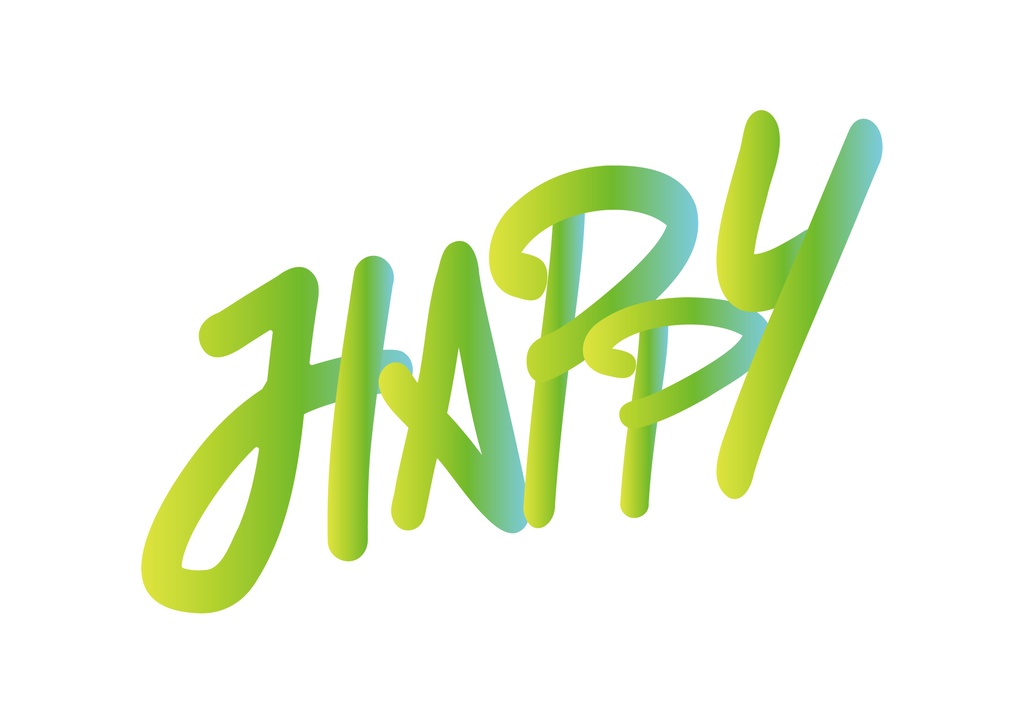
【商用可・無料配布】手書きの衝動をデザインに!「タギングフォント」
こんにちは! 私たちは、名古屋市星ケ丘にあるクリエイティブ特化のB型就労継続支援事業所「でじるみ名古屋星ケ丘」です。 この度、当事業所の利用者さんが心を込めて制作した、オリジナルの手書きフォント「タギングフォント」を無料配布させていただくことになりました! ◆ フォントの特徴 ストリートカルチャーから飛び出してきたような、ラフで力強い手書き感が魅力のフォントです。 一文字一文字にクリエイターの個性が光り、あなたのデザインにクールなアクセントとインパクトを与えます。 《こんなシーンにオススメ!》 動画のテロップやYouTubeのサムネイル 同人誌のタイトルや奥付 イベントのフライヤーやポスター オリジナルのTシャツやグッズ制作 SNS投稿の画像加工 など あなたのクリエイティブな活動の相棒として、ぜひご活用ください! ◆ でじるみ名古屋星ケ丘について 私たちは、デザイン、イラスト、動画編集など、一人ひとりの「好き」や「得意」を仕事につなげるサポートをしています。 このフォントは、利用者さんが日々スキルを磨き、情熱を注いで作り上げた努力の結晶です。 このフォントをダウンロードし、使っていただくことが、利用者さんたちの自信と、さらなる創作活動への大きな励みになります。 もしよろしければ、商品ページの「スキ!」やSNSでのシェアで応援していただけると、スタッフ・利用者一同、大変嬉しく思います。 ◆ 利用規約 皆さまに安心して楽しく使っていただくための、簡単なお約束です。 OKなこと 個人利用、商用利用 動画、印刷物、Webサイト、同人誌、グッズなどあらゆる制作物での使用 フォントの変形・加工(縁取り、変形など) NGなこと フォントデータそのものの再配布、販売、譲渡 公序良俗に反する目的、誹謗中傷目的での利用 その他 クレジット表記は任意です。もし表記していただける場合は「フォント:でじるみ名古屋星ケ丘」のように記載していただけると嬉しいです。 フォントを使用して発生したいかなるトラブルについても、当事業所は責任を負いかねます。予めご了承ください。 ◆ 収録文字・ファイル形式 収録文字:アルファベット(大文字) ファイル形式:OTF / TTF 最後までお読みいただき、ありがとうございます。 このフォントが、あなたの素敵な作品の一部になれることを心から願っています。